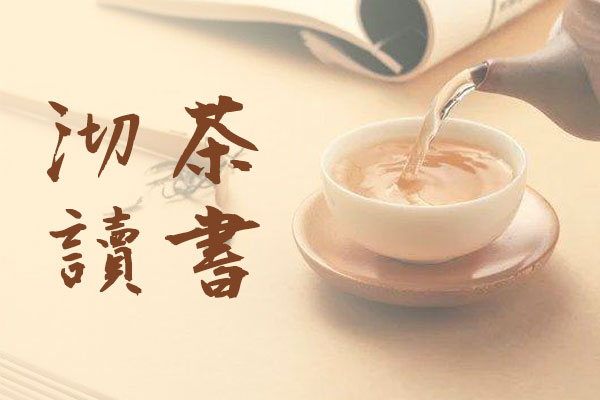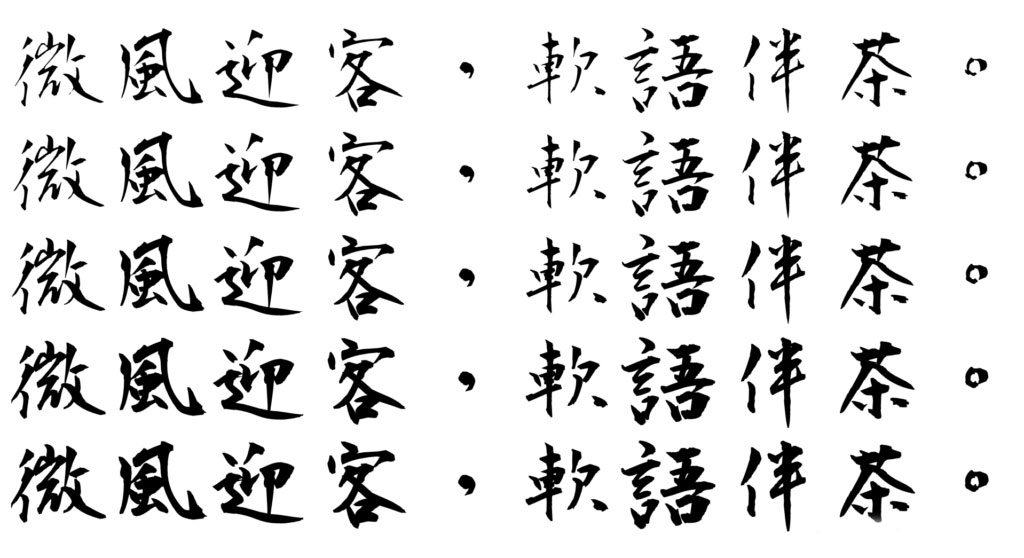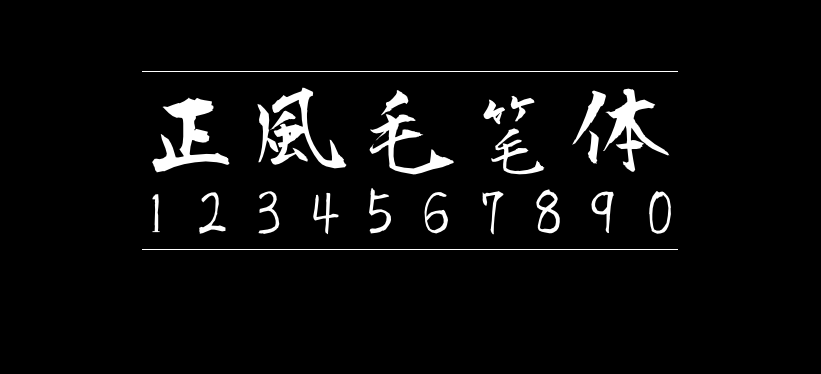
正风毛笔体
正风毛笔体(正風毛筆 MasaFont)是中国台湾的设计师Max基于衡山毛笔行书进行字符增补的一款毛笔字体。衡山毛笔行书字体是来自于日本书法家青柳衡山,文字加符号数共7,582字,经过Max的补充文字加符号数共23,699字。繁体字比较全,简体字型有部分缺字现象。
相较于正风毛笔字体的师兄莫大毛笔体,正风在个性上就随性很多,也造成有部份的一些字很粗,而有些字极细。原作者的“木”、“米”、“禾”系列常常会少一撇,是正常的,第一次看到会觉得有点怪,但是看久就会习惯了。
由于是正风毛笔字体并非原作者的亲自手写,而是使用人工智能的方式在学习原有字形的基础上进行的增补。新加入的字在风格上,虽然力求一致,但是难免会与原作者会有一些不同。有很多很多字补的“超级丑”的,几乎大部份的字都有改善空间,如果有好心人有重做那些丑到爆(或长像怪怪)的字,可以Email(weng.32002@gmail.com)发给Max,感谢!
正风毛笔字体包含了5个字重。原本的衡山毛笔行书字体放在Regular字重里,通过程序自动产生ExtraLight、Light、Medium、Bold等新的字重。Light字重是把原本的衡山毛笔行书微微调细一点点。在ExtraLight的字重裡,可能会因为笔划太细造成某些笔画消失。在Medium和Bold的字重里,可能会因为笔划太粗造成某些笔画重叠难以识别,有粗体字的需求,可以先尝试使用Bold字重看看,如果发现效果不如预期,再改用Medium字重。不能确定自动产生出来的字重里每一个都是完整的字,毕竟程序误判是常有的事情,所以不是在Regular字重里的笔划可能会消失。